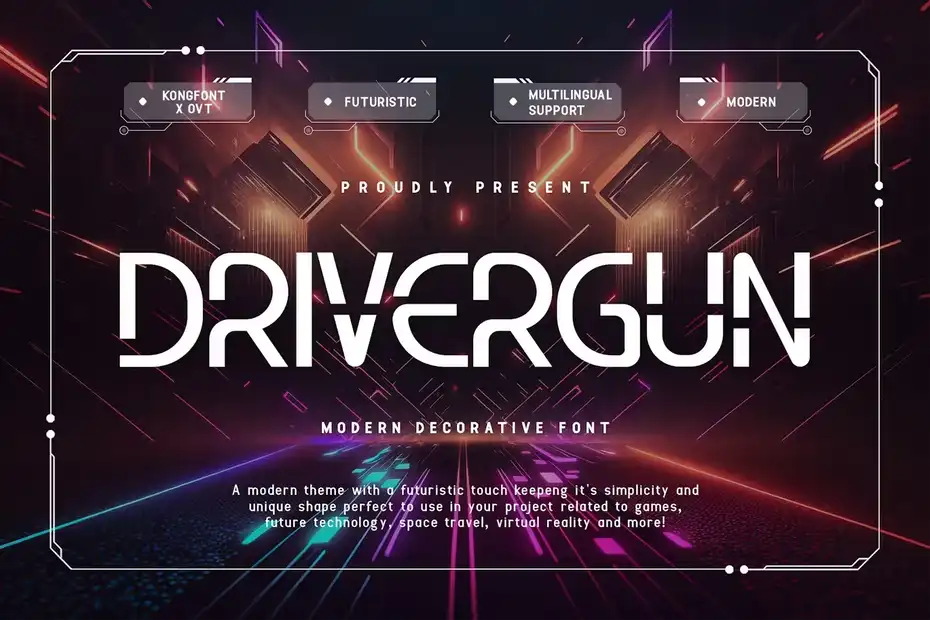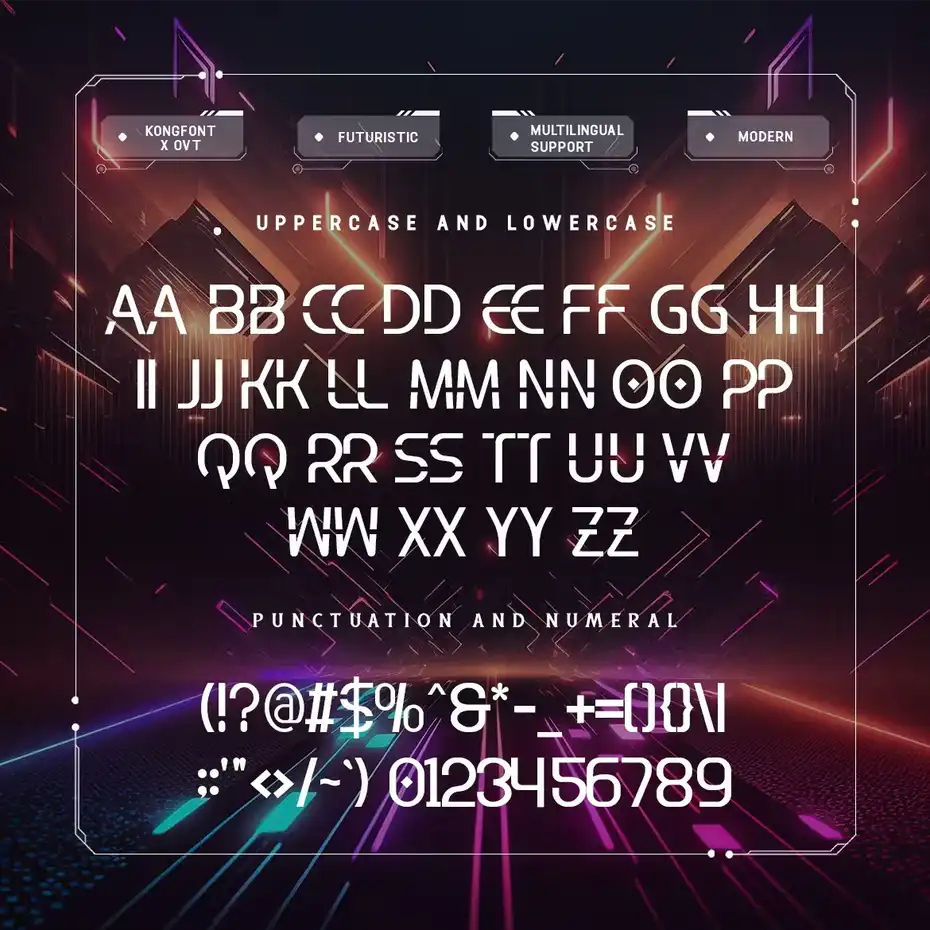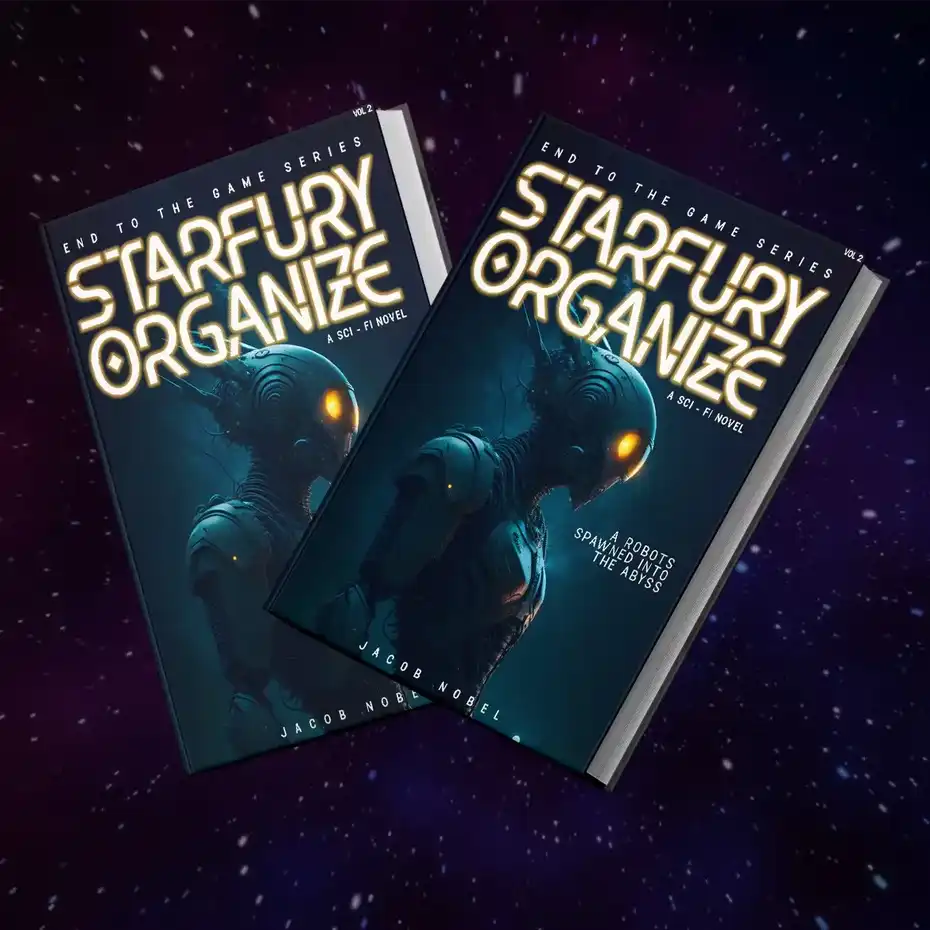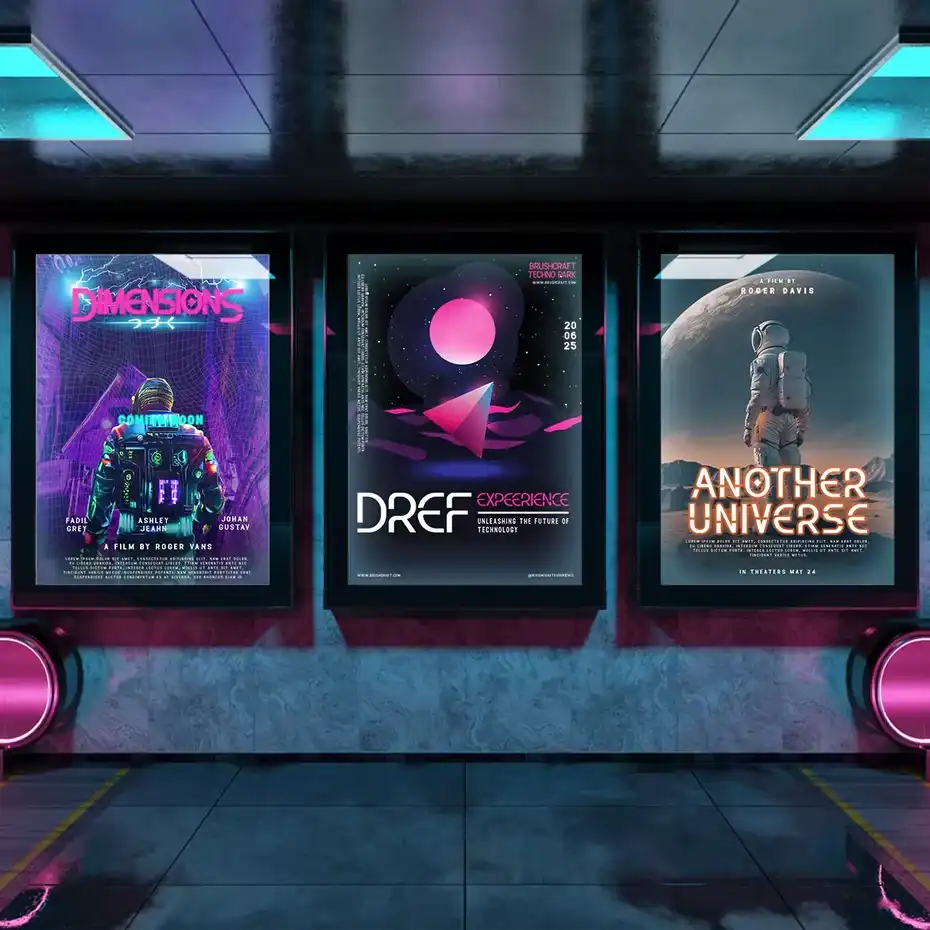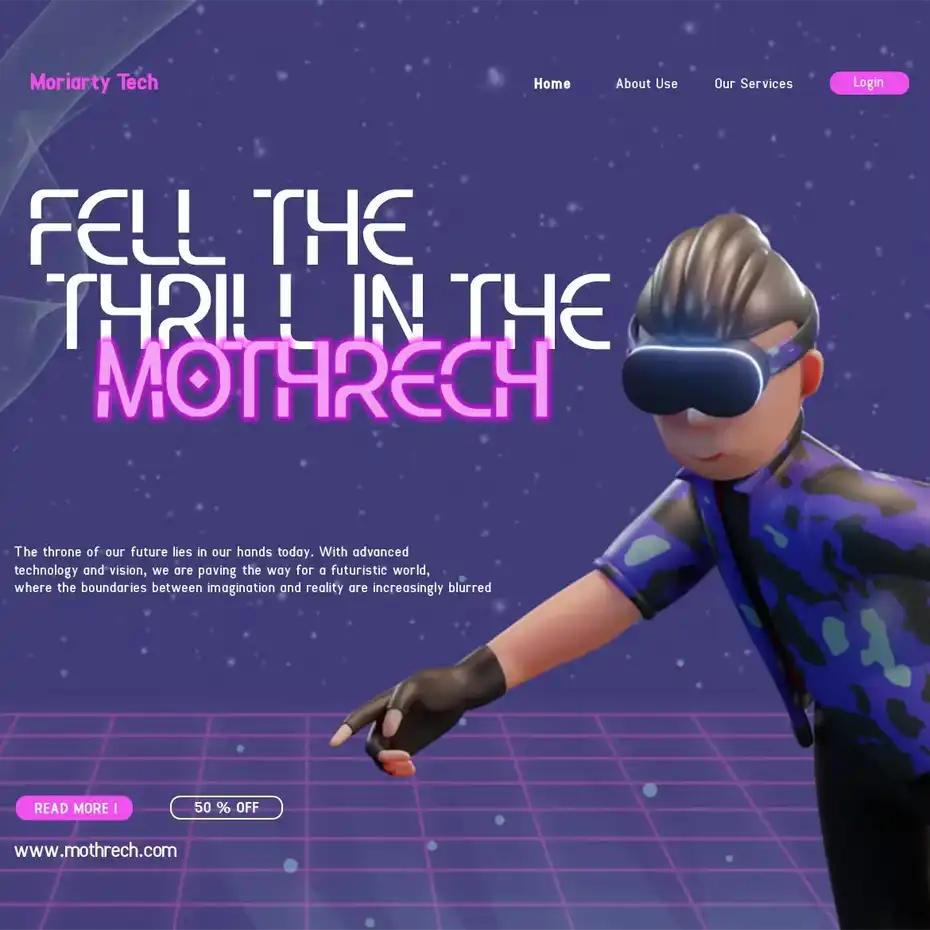
دانلود فونت تزئینی مدرن Drivergun – Modern Decorative Font
دانلود فونت تزئینی مدرن Drivergun – Modern Decorative Font : این مطلب شامل یک فونت انگلیسی مدرن است که برای برندسازی متمرکز بر فناوری، رسانه های دیجیتال پویا و پروژه های علمی تخیلی مناسب میباشد.